Die Neumen geben nur an, ob ein Ton höher oder tiefer als der vorherige liegt — über die genaue Tonhöhe, Tempo oder Rhythmus wird kein Wort verloren. Da diese Notation fast ausschließlich in Klöstern verwendet wurde, reichte das aus: Die Melodie wurde unter den Brüdern und Schwestern beim täglichen Gottesdienst mündlich weitergegeben, die Neumen halfen lediglich, sich nicht im Kontur zu verirren.
Neumen
Neumen sind eine frühe Form, Melodien aufzuschreiben — geboren im klösterlichen Gottesdienst des frühen Mittelalters und gedacht als bloße Gedächtnisstütze für das, was die Brüder ohnehin im Ohr trugen.
9.–13. Jahrhundert
Die Anfänge der Notenschrift
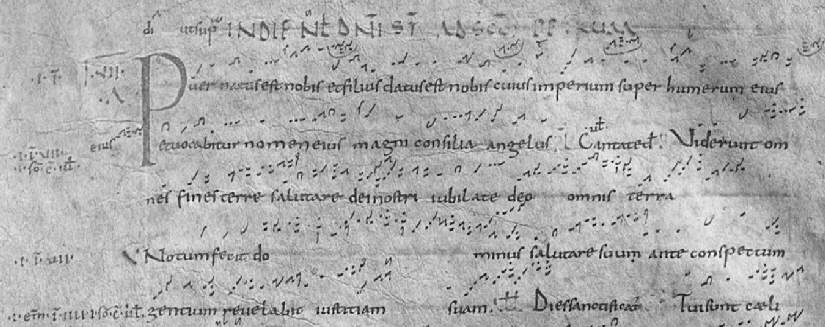
Klösterliches Gedächtnis
Bögen, Punkte und Striche
Über dem lateinischen Text schwingen kleine Zeichen — Punkte, Häkchen, Bögen. Sie zeigen dem Sänger, wohin die Stimme wandert, nicht aber, wie weit. Das Gedächtnis trug die Tonhöhe, die Neumen halfen, sich nicht zu verirren.